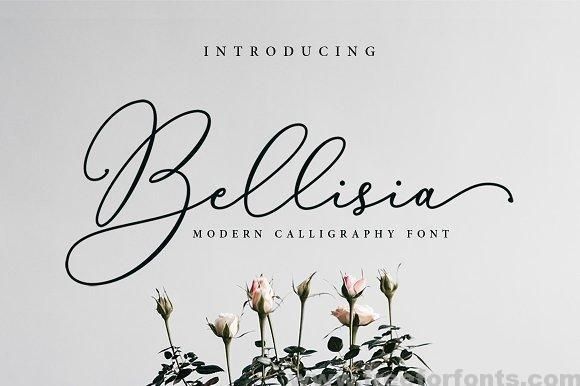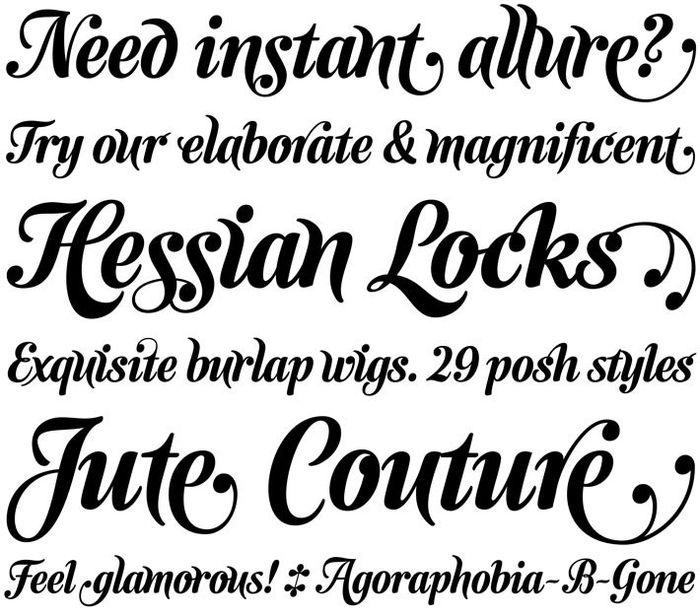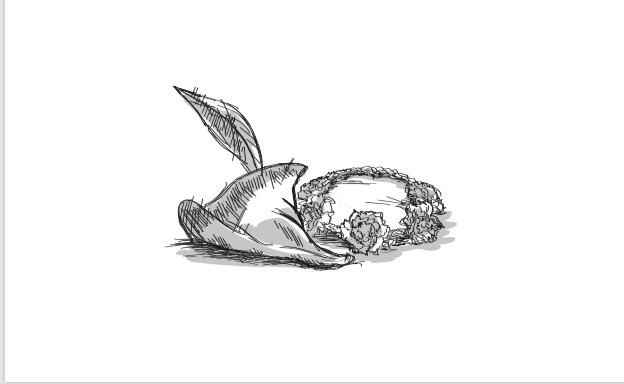
Quale font per questo logo?
Quale font per questo logo? 1 Ciao a tutte!
Questo è il logo che abbiamo scelto per partecipazioni e menù ... vi piace??Ma sopratutto?qualche idea per il Front??? Io zeroool😱😱😱
Ovviamente il tema é Robin Hood e lady Marian
Secondo me si! 🥰☺️
Speriamo venga bene
Bellisisma scelta 🥰
Che carino, mi piace molto
😊😊😊😊 mi farò venire in mente qualcos a
Siiiii avevo capito 😊 🔝🔝🔝🔝
Eh lo so ma l’idea era più Robin del film
Poi essendo il verde il colore che ho scelto ... si abbina proprio
Anche io quoto Viviana.
Comunque bellissimo tema, originale! Mi piace!
Però non Robin Hood della Disney
Bellissimo tema, mai sentito fino ad ora!!
Grazieeeeeee però non il cartone disney
Fantastico il tema non L avevo mai visto finora brava 🥰
Si esatto
Una cosa pulita
Sisi infatti é disegnato amano da un nostro amico grafico e riportato su pc.... io volevo fare qualcosa di pulito ... i colori sono bianco e verde scuro e champagne .. quindi giocare con questo tre colori ma non aggiungere molte cose costose oltre al logo
Io metterei un font di scrittura a mano, non dritta ma obliqua e non troppo spessa. 😁😘
Si anche io ero piu orientata al
Moderno
Quale font per questo logo? 2io ci vedrei bene qualcosa del genere e magari dei fiori in stile acquerelli.. O degli alberi 😊
Io oserei coi caratteri disney 😻
Si carattere e magari qualche aggiunta di decorazione
Io userei lo stesso carattere trovi sulla locandino di robin Hood
Intendi per il carattere con cui scrivere?